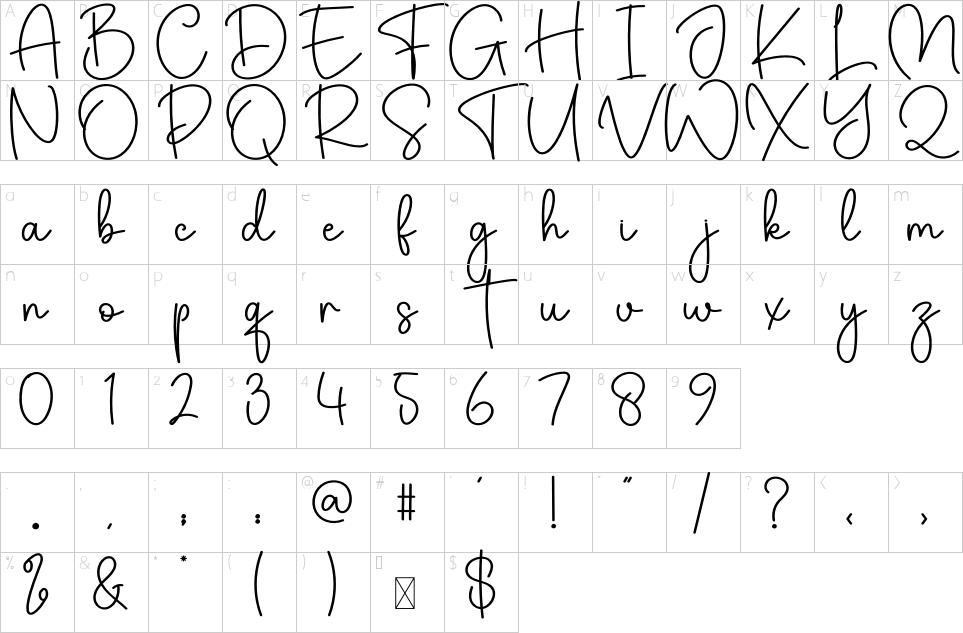
A fonte Ghostinger é uma opção ótima para quem busca personalidade e graça para seus projetos digitais, seja eletronicamente ou impresso. Desenhada pelo designer desconhecido scratchones, esta fonte oferece um toque único que torna qualquer projeto mais atraente e distintivo. Aproveite o benefício de ter Ghostinger disponível tanto em sistemas operacionais Windows quanto Mac, facilitando seu uso sem interrupção nas suas tarefas. Com uma baixa popularidade de apenas 635 downloads, esta fonte gratuita é um tesouro valioso para quem quer manter seus projetos limpos e modernos. Seja você um designer gráfico, web designer ou qualquer profissional que trabalha com texto em seu trabalho, Ghostinger oferece a opção perfeita para dar um toque especial à sua identidade visual. Não espere mais! Baixe Ghostinger agora e deixe sua marca de uma maneira única e imediata.